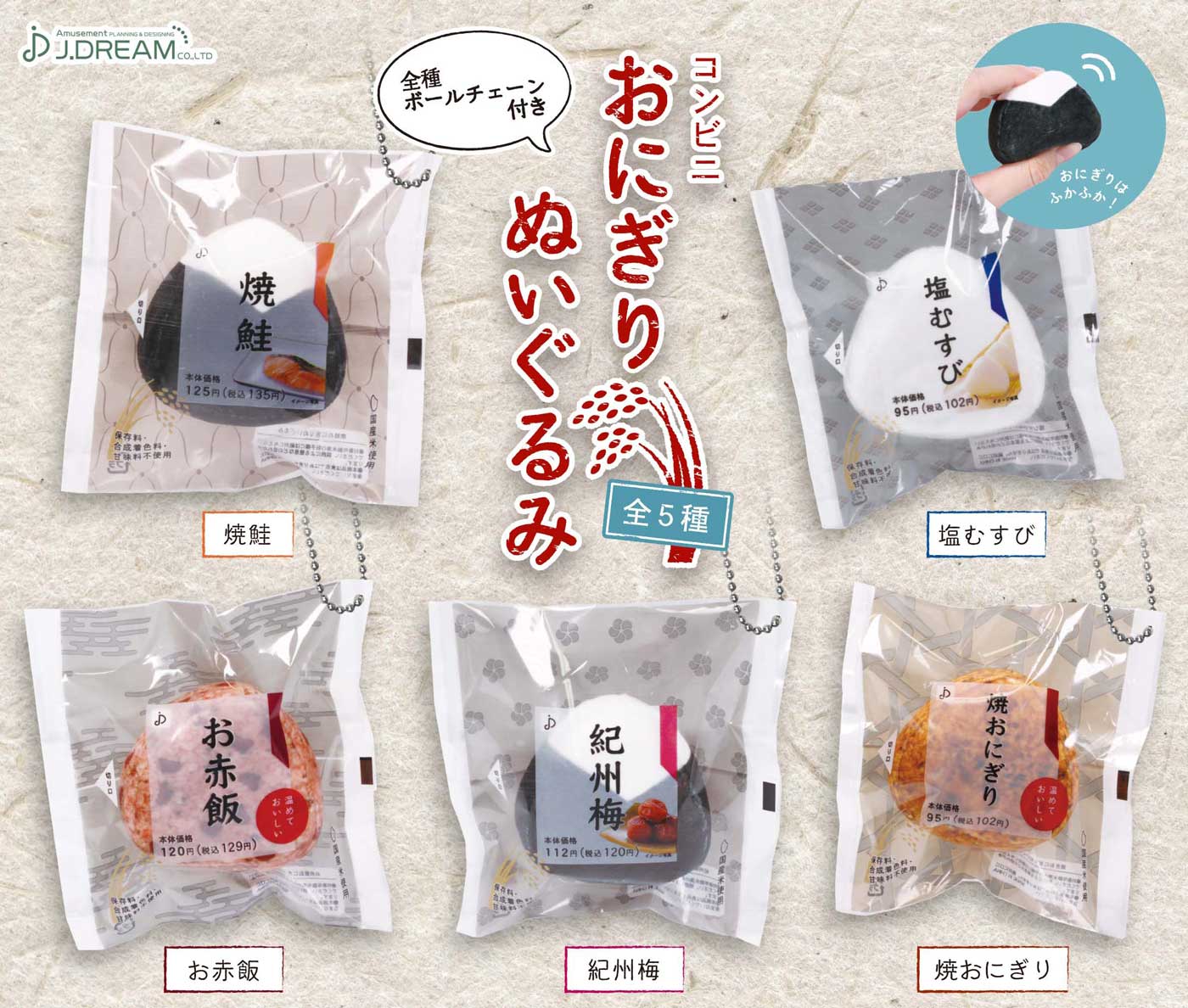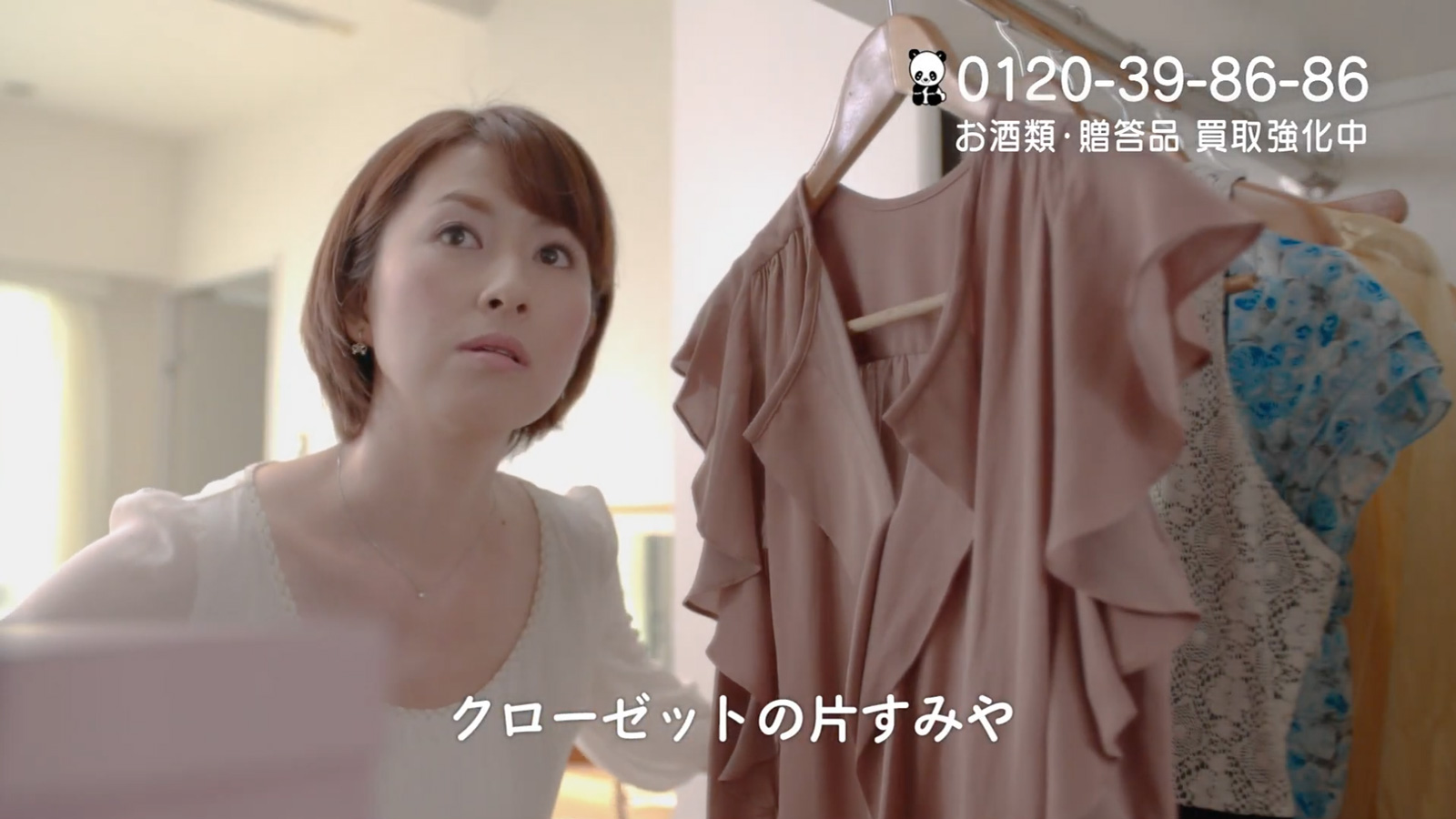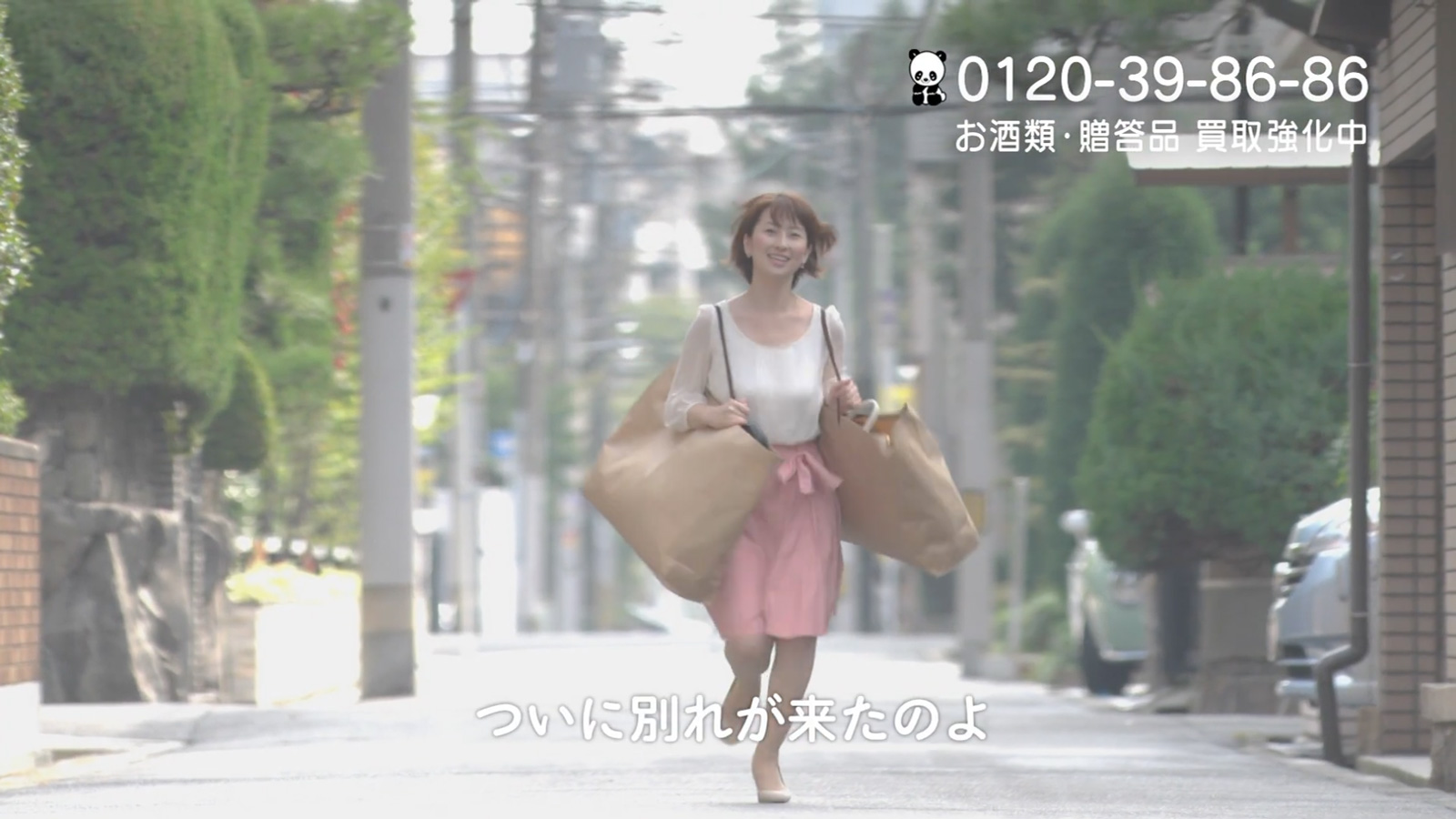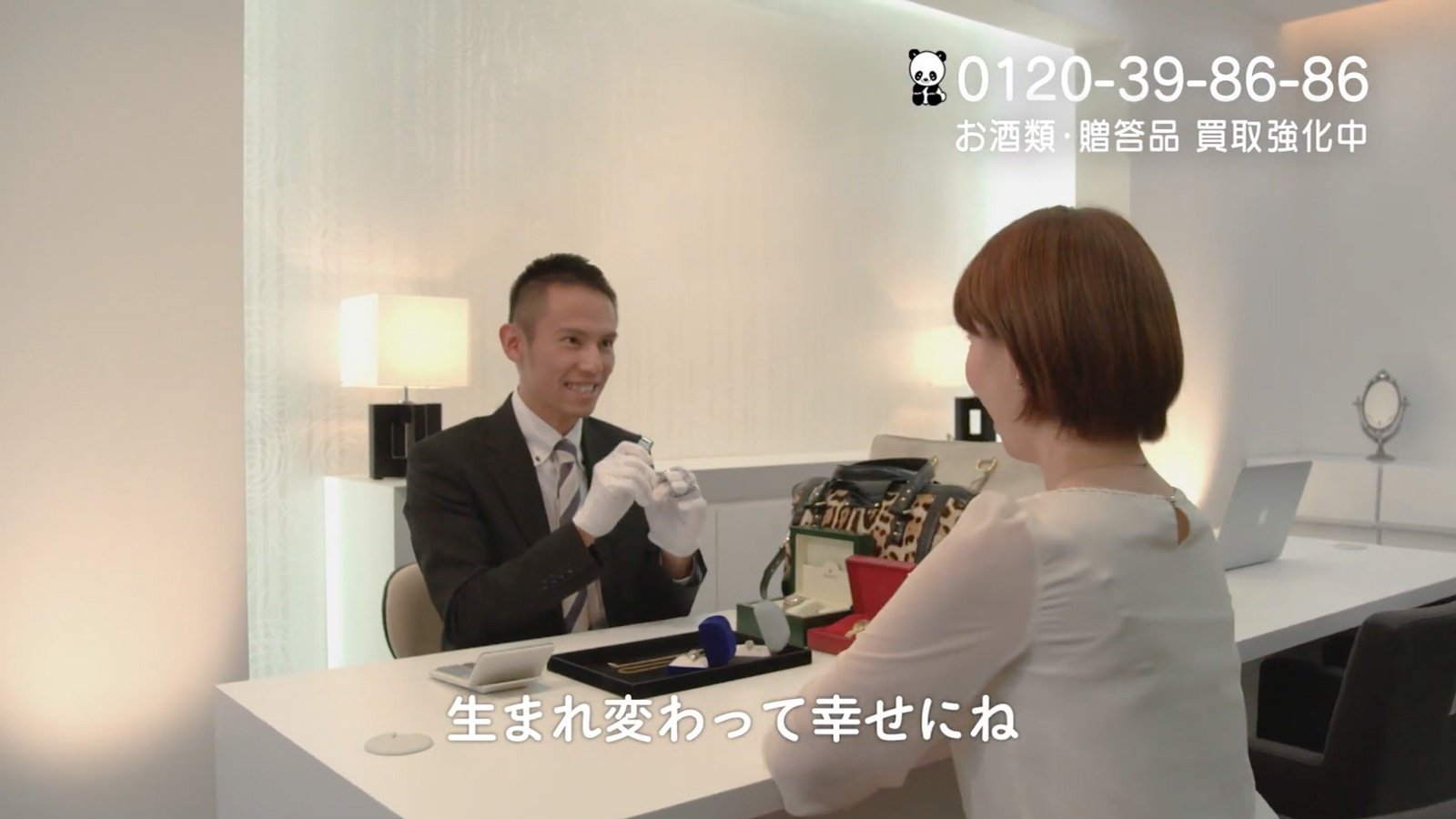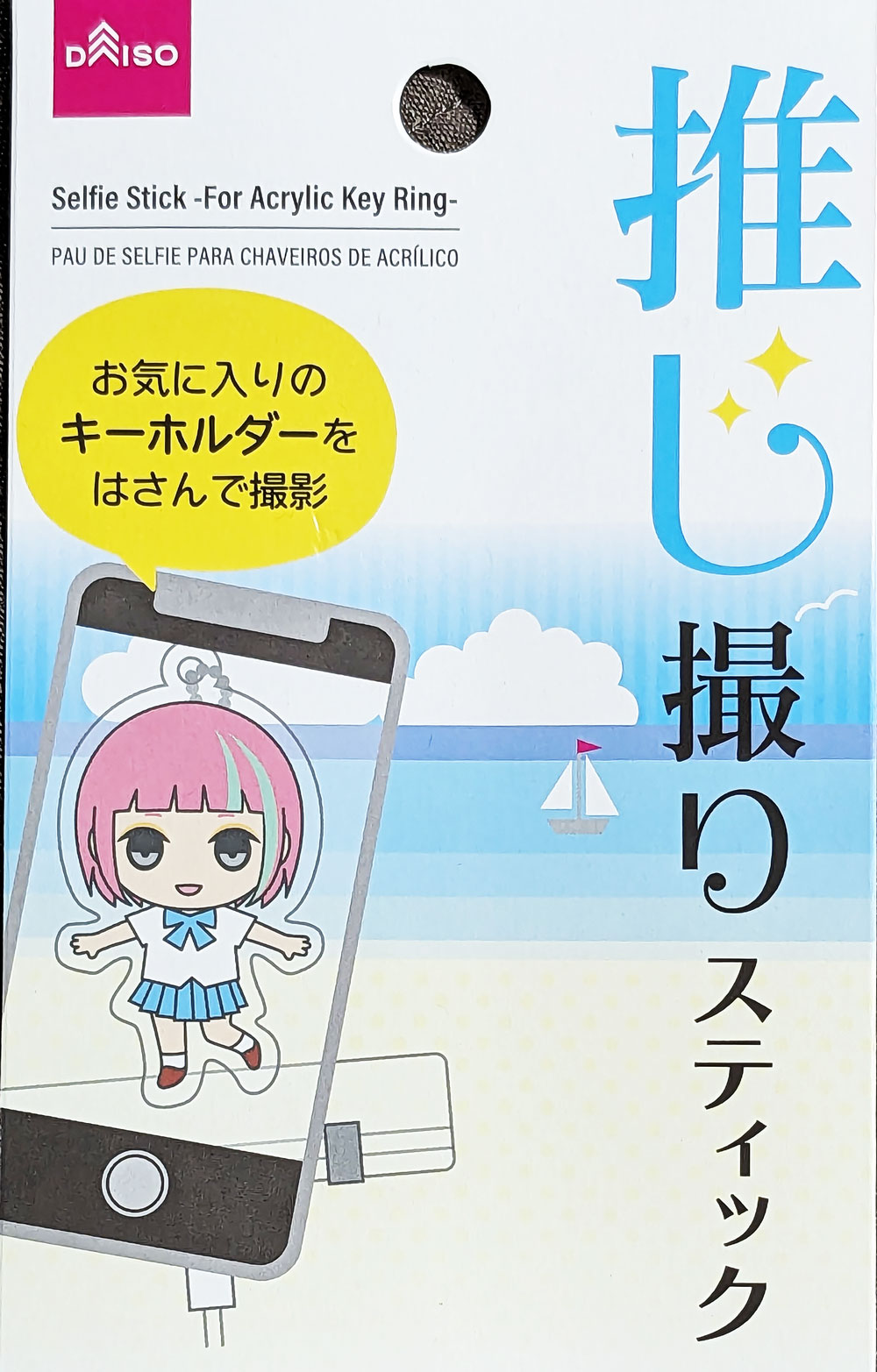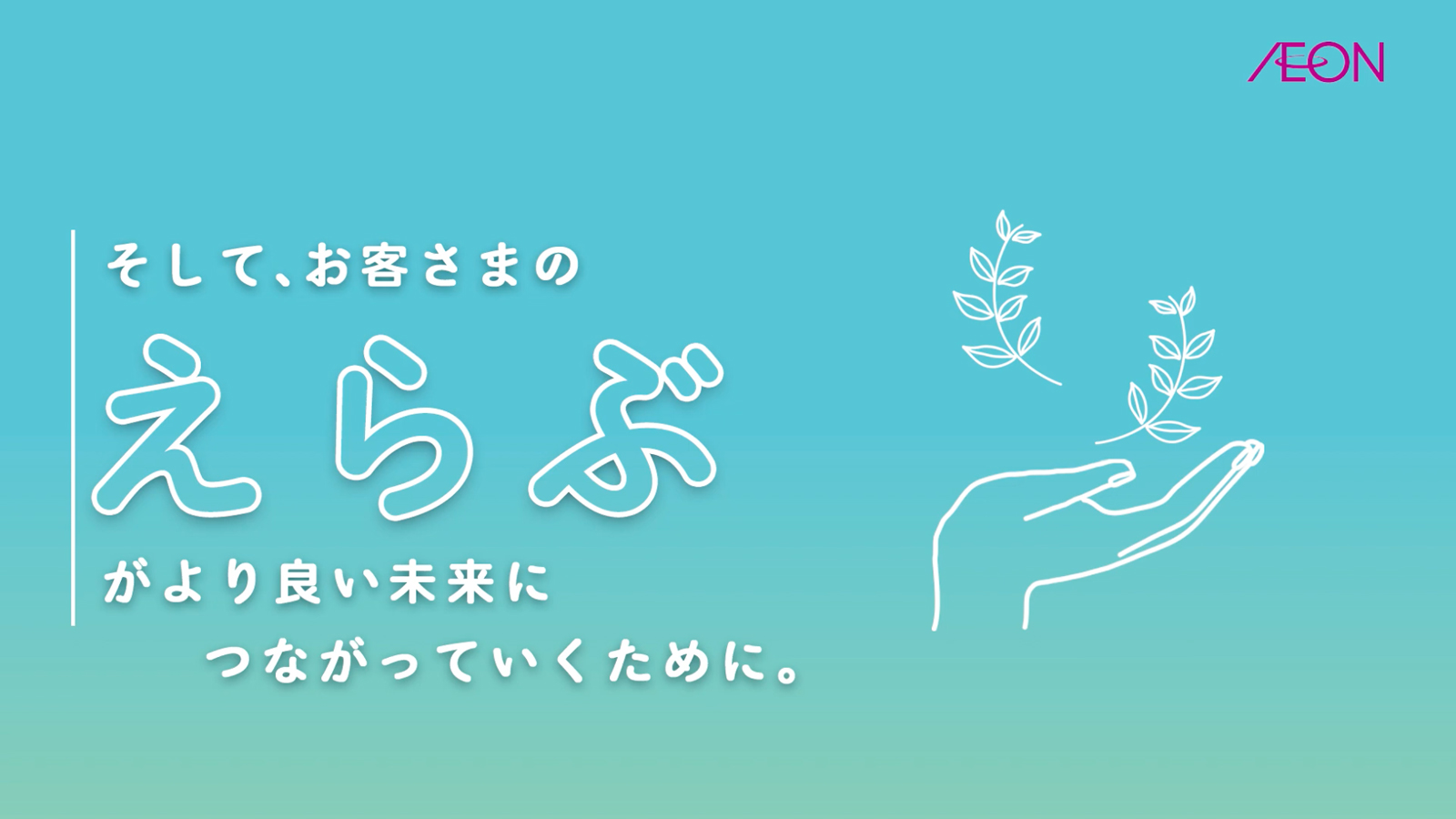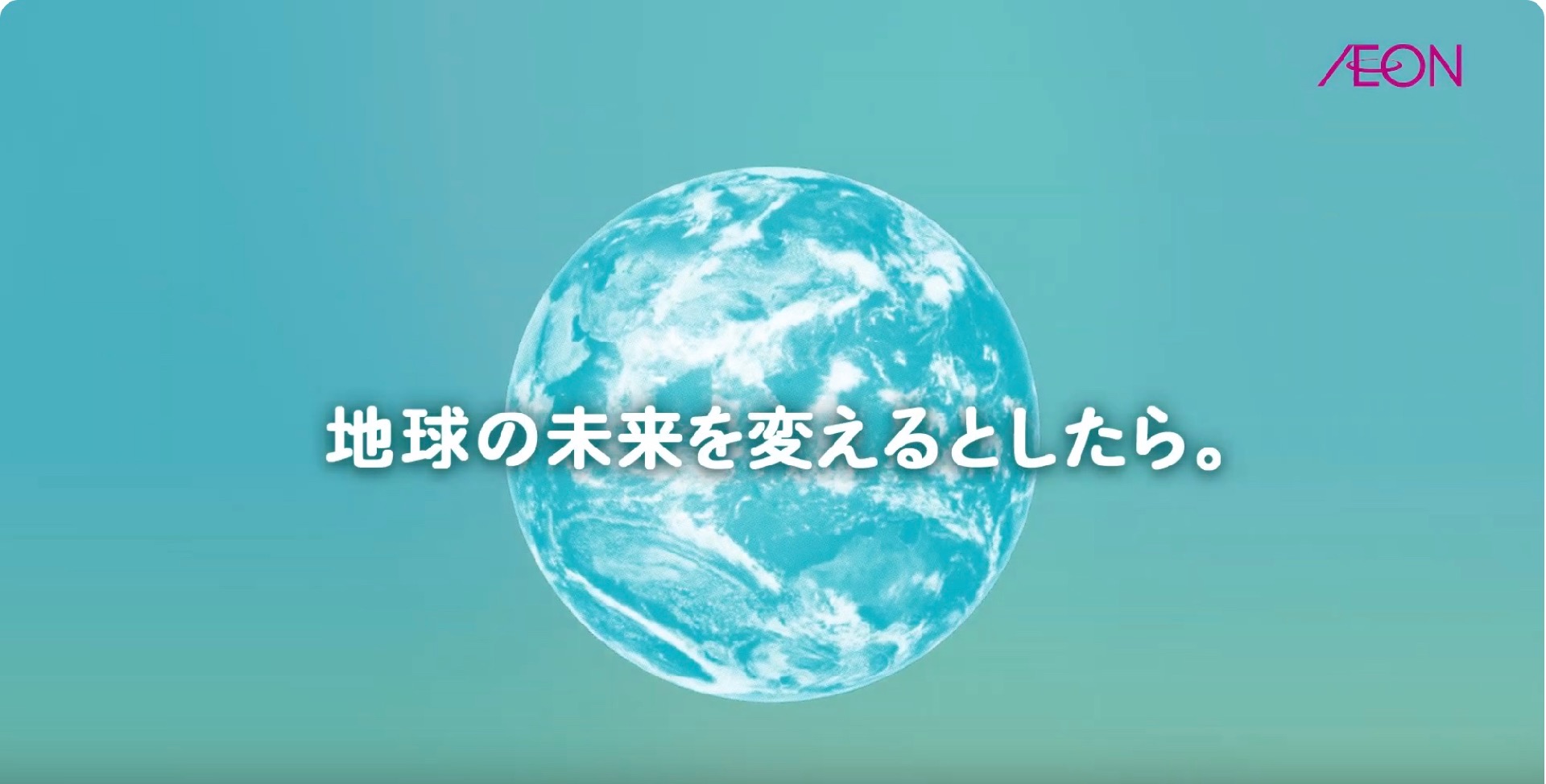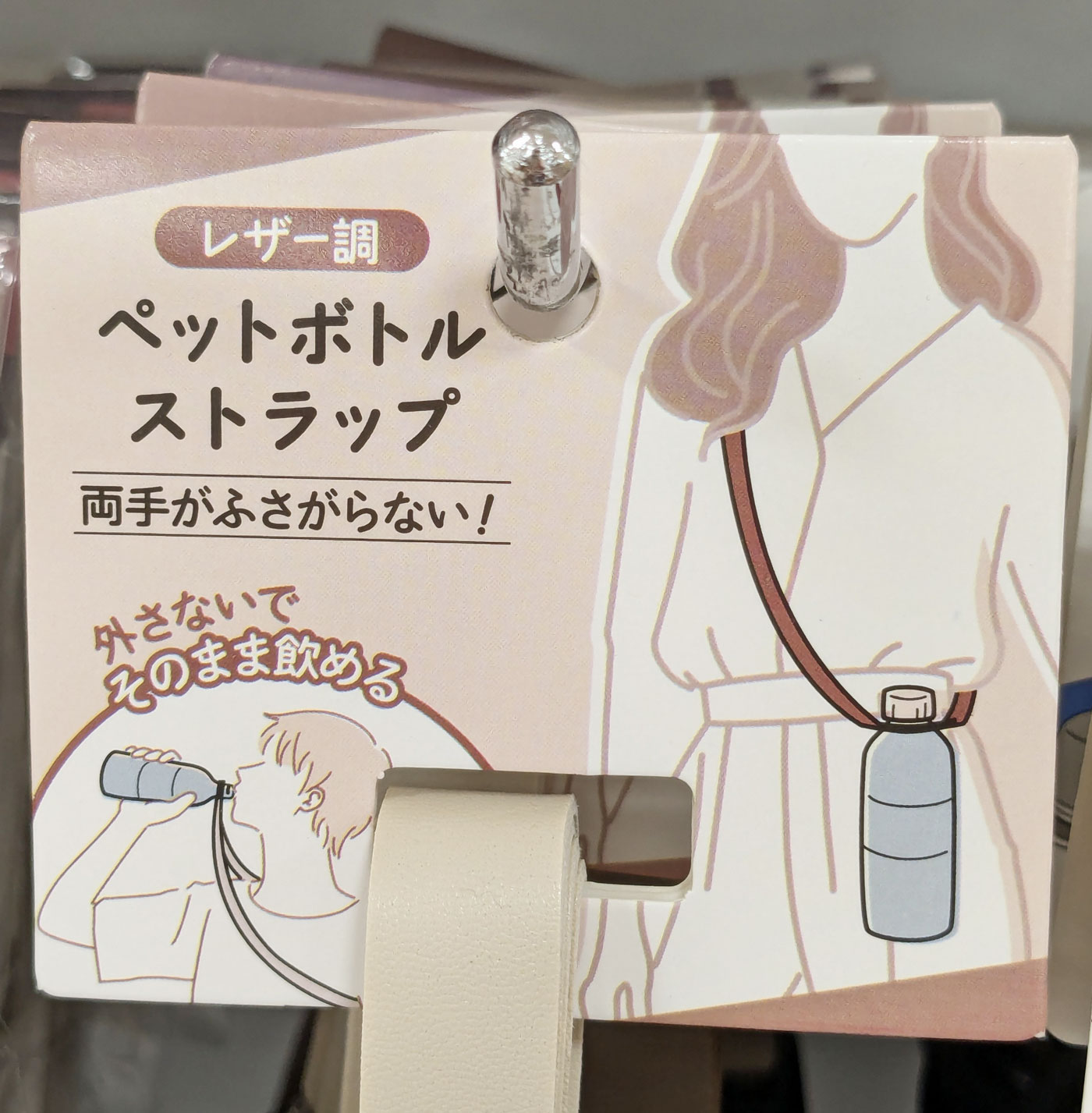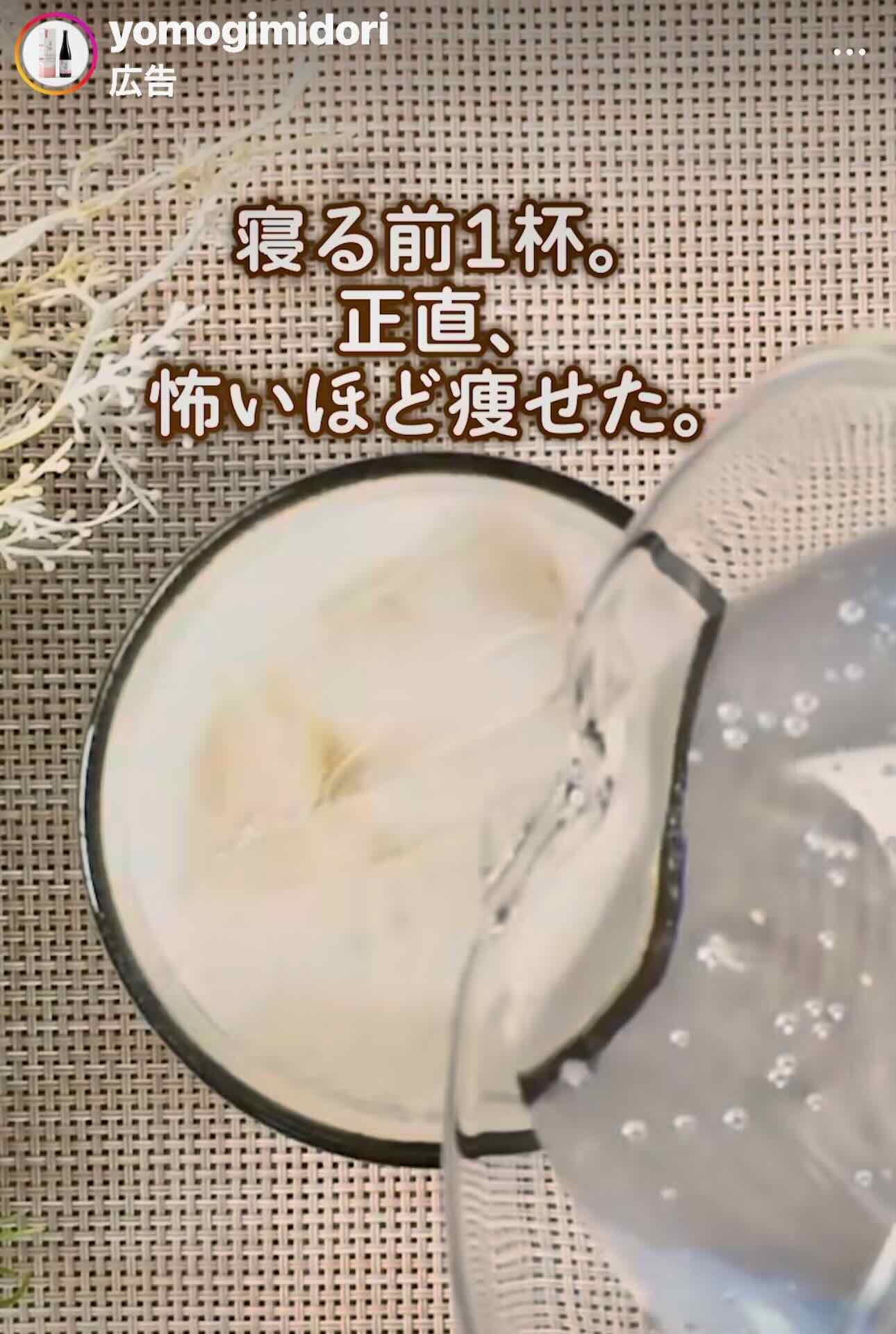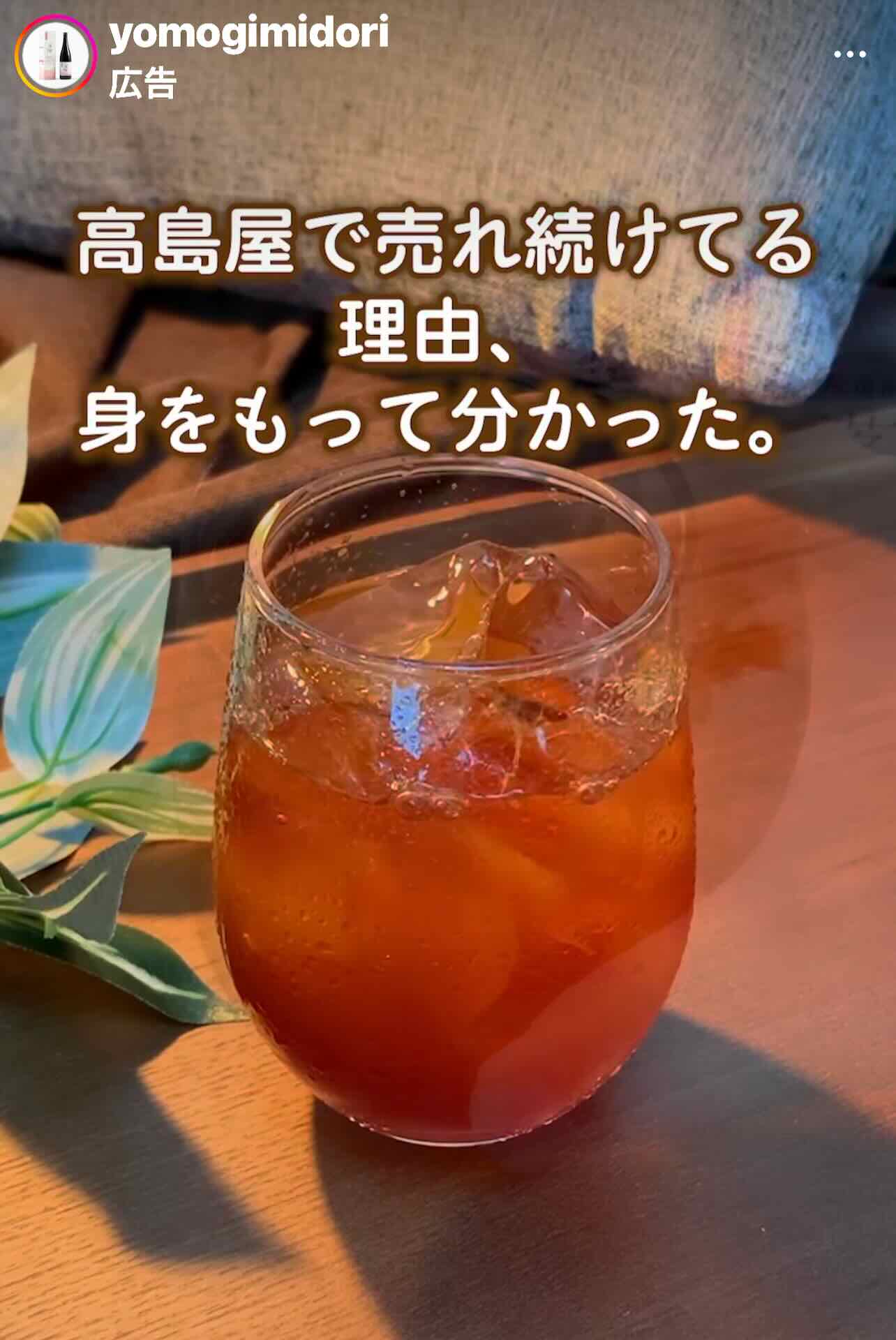
レラ・キャピレラ・ニタラゴレラ・墨東レラ・わんぱくレラ
日テレNEWSの動画 takumi
「日テレNEWS」のYouTubeチャンネルにアップされている動画で墨東レラが使われていました。
これも。
サムネ?画像 さとうゆたか
JTBの「にっぽんの祭り・花火特集」
墨東レラ-6かな?
広告画像 さとうゆたか
レラは、クセのないプレーンな丸ゴシック書体。
あまり目立つことはないが、言葉の意味に余分なイメージを付けず、やさしく伝えてくれる…。
すこし平べったく変形されている。
全体画像。
広告画像 さとうゆたか
このフォントは墨東レラ。
健康食品のようだ。
これも。
まだある。
もうひとつ。
住宅の広告 さとうゆたか
墨東レラ5の使用例。
親しみやすい丸ゴシックの漢字と、真面目で安心なイメージのかな書体「墨東丸」が、住宅という高価な商品の広告にうまくハマっている気がする。
コンビニのPOP さとうゆたか
墨東レラの使用例。
セブンイレブンの冷凍食品コーナー。
百均の商品 takumi
百均で見かけた「墨東レラ」です。
写真に写ってる文字はすべて墨東レラですが、機械的に太らせてるところがありますね…。